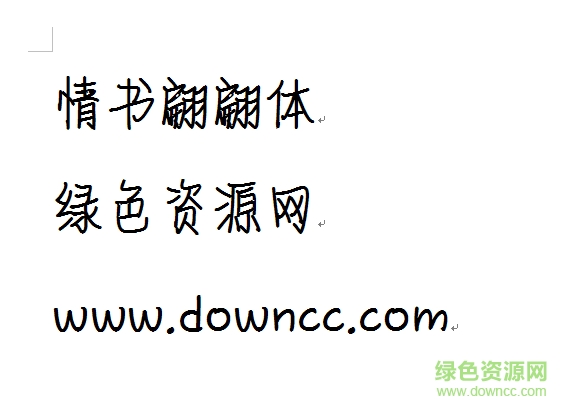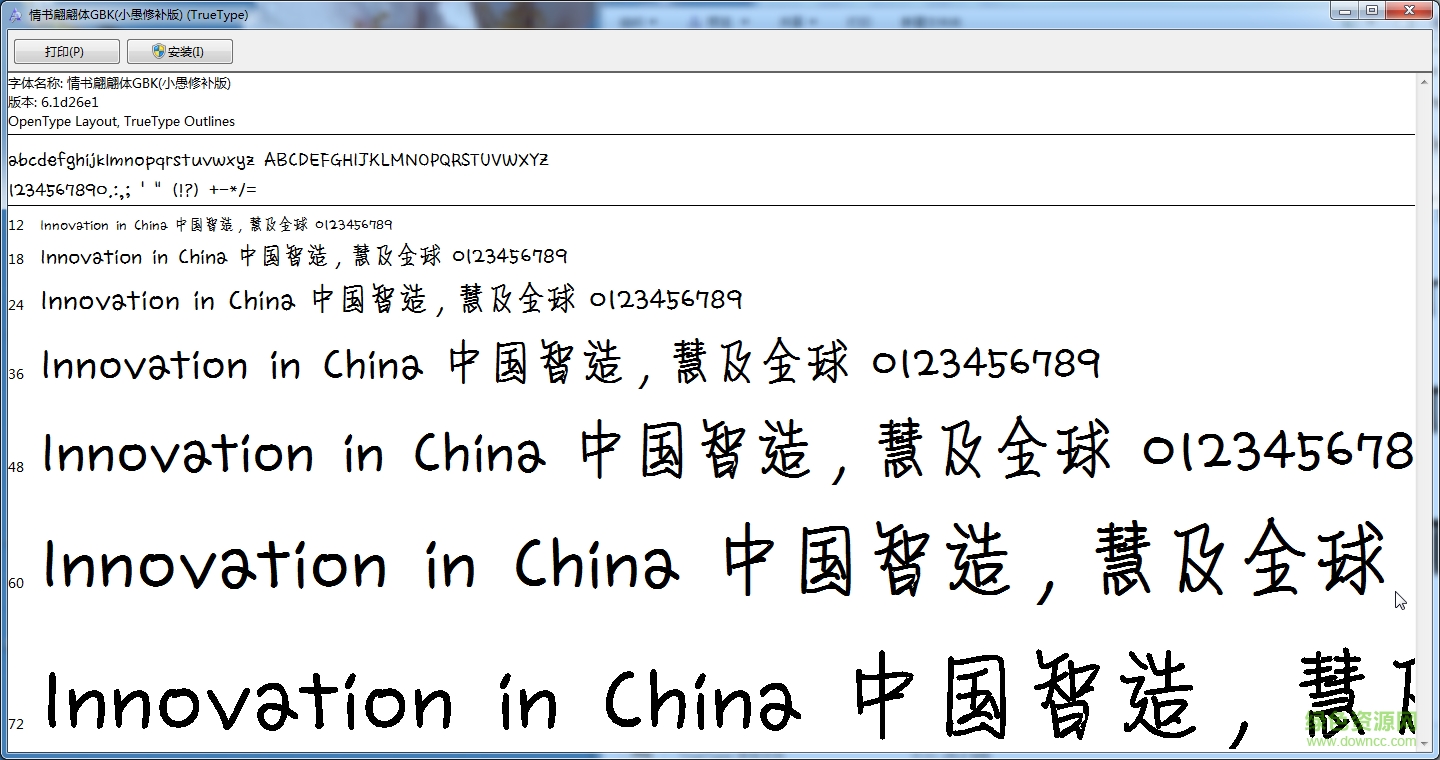
情書(shū)翩翩體ttf
情書(shū)翩翩體完美版ttf是一款字跡清秀、瀟灑飄逸的電腦端字體,是一款適合情侶間傳情達(dá)愛(ài)的好用工具,軟件使用非常簡(jiǎn)單,喜歡這種字體的朋友就來(lái)綠色資源網(wǎng)下載吧!
情書(shū)翩翩體是一個(gè)有溫度的字體,深受許多網(wǎng)友的喜愛(ài),無(wú)論是情侶間的情書(shū)撰寫(xiě)、個(gè)人心情會(huì)議記錄還是親人間的聊天談心,都能給你最愉悅的打字享受。本次綠色資源網(wǎng)小編為大家?guī)?lái)這款有溫度有情懷的字體ttf,希望大家喜歡!